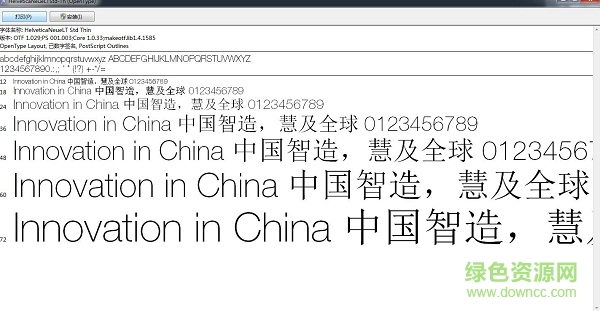
helveticaneueltstd-th字體是這套字體里面最細的一款,現(xiàn)代大氣,沒有任何手工的痕跡,十分地標(biāo)準(zhǔn)化,適合用在時尚品牌、電子屏幕等方面,歡迎免費下載!
helveticaneueltstd字體優(yōu)缺點
【優(yōu)點】
Helvetica的出現(xiàn)就像一股清流,它去掉了多余設(shè)計,關(guān)注字體本身的結(jié)構(gòu),給設(shè)計界帶來更優(yōu)質(zhì)的可選方案。
【缺點】
Helvetica的設(shè)計理念是一致、去個性,字母的整體造型都偏圓,因此缺乏閱讀韻律